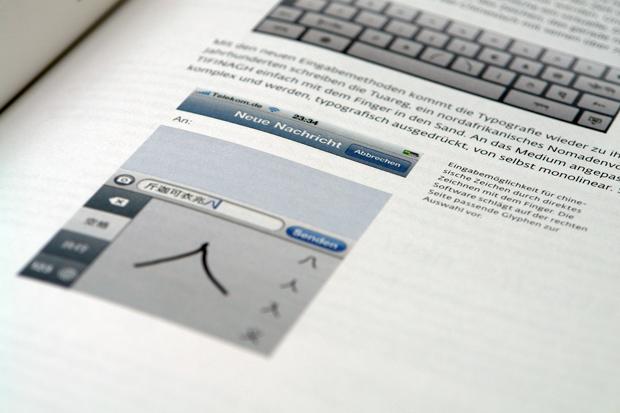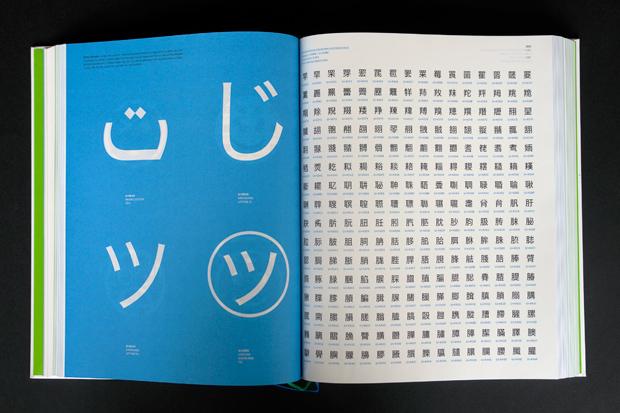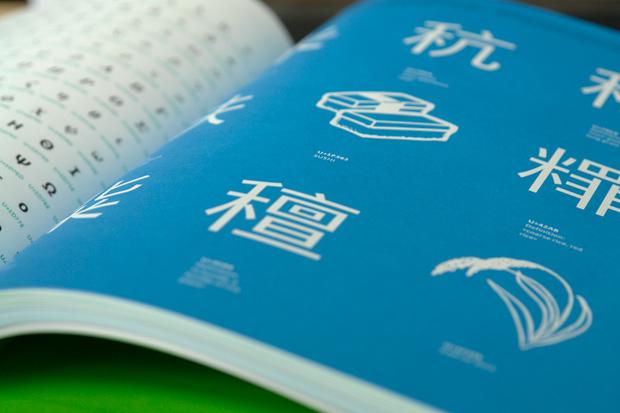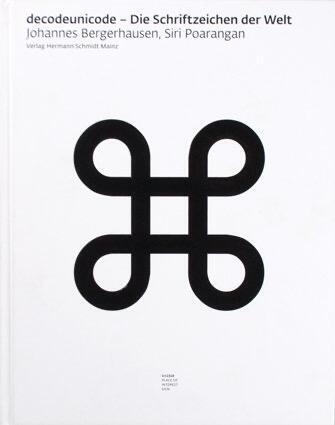
Das Buch Decodeunicode geht auf das gleichnamige Online-Projekt zurück, das an der Fachhochschule Mainz unter der Leitung von Professor Johannes Bergerhausen zusammen mit der Diplom-Designerin Siri Poarangan konzipiert und entwickelt wurde. Seit 2005 werden hier in Wiki-Form Informationen zu allen Unicode-Zeichen gesammelt.
Das 656 Seite starke Buch druckt nun tatsächlich alle 109.242 Schriftzeichen des aktuell gültigen Unicode-Standards 6.0 ab und reichert die Abbildungen mit umfassendem Hintergrundwissen zu Unicode an. Insbesondere die ersten 60 Seiten des Buches sollten zukünftig als Pflichtlektüre der digitalen Typografie gelten. Dieser Teil schlägt in die gleiche Kerbe, die ich mit meinem Zeichen-setzen-Buch und vielen Artikeln hier auf Typografie. info verfolge. Schriftsatz ist heute digital und das Verständnis von Zeichenkodierungen und den Eingabemöglichkeiten am Rechner sind somit essentiell. Viele Typografie-Bücher unterschlagen dies auch heute noch und beschränken sich auf die Vermittlung von typografischem Wissen aus der vordigitalen Zeit. Das Decodeunicode-Buch erklärt diese Grundlagen in sehr einfacher und übersichtlicher Weise und jeder, der mit Schrift professionell am Rechner arbeitet, sollte über dieses Wissen verfügen.
Der größte Teil des Buches widmet sich dann der Abbildung aller heute gültigen Unicode-Zeichen auf 434 Seiten. Ausgewählte Zeichen werden auf 96 Seiten einzeln und mit zusätzlichen Erklärungen separat vorgestellt. Im Prinzip hat ja jeder Computer-Nutzer schon einen »Unicode-Browser« auf seinem Rechner. Am Mac heißt er Zeichenpalette und am PC Zeichentabelle. Aber nur die Buchform von Decodeunicode lädt wirklich zum Stöbern, Blättern und Schmökern ein. Hier beweist das Buch auch in der digitalen Welt noch einmal seine volle Stärke.
Im Anhang des Buches folgt dann noch eine Übersicht der Schriftsysteme der Welt, einschließlich solcher, die noch nicht im Unicode enthalten sind. Dieser (zu unrecht etwas unscheinbar im Anhang versteckte) Teil geht auf ein Forschungsprojekt an der University of California, Berkley zurück und ist in dieser übersichtlichen, leicht zugänglichen Weise zumindest in Deutsch sicherlich auch einmalig.
Fazit: Bücher zum Thema Unicode gibt es bereits einige. Meist sind sie nur in Englisch verfügbar und richten sich vor allem an Software-Entwickler. Decodeunicode bietet dagegen einen typografischen und visuellen Zugang zum größten Zeichensatz der Welt. Und dies macht das Buch gleichermaßen einzigartig und nützlich. Wünschen würde ich mir jedoch auch wieder einen »digitalen« Zugang zu den 434 Code-Seiten. Zum Beispiel eine Online-Suchfunktion, die mir über eine Volltextsuche nach Unicode-Name die Seite im Buch ausgibt.
Insbesondere die begleitenden Texte im Buch machen es aber besonders wertvoll und empfehlenswert. Insofern schließe ich mir gern Jürgen Sieberts Meinung an: »Dieses Buch ist der Hammer«.